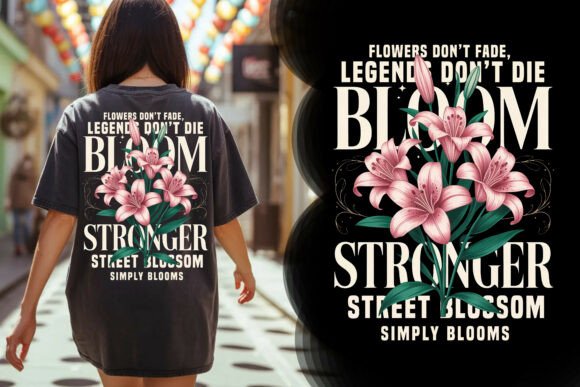
Bloom Stronger Floral Typography Tee
Bloom Stronger Floral Typography Tee – Avaliação Completa
Se você procura uma peça que una estilo contemporâneo, mensagem inspiradora e qualidade de impressão impecável, a Bloom Stronger Floral Typography Tee é a escolha certa. Este T‑shirt destaca‑se não apenas pela estética, mas também pelo storytelling visual que ele carrega: flores de lírio delicadas combinadas com tipografia ousada que celebra o crescimento pessoal e a resiliência.
Principais Pontos Positivos
- Design exclusivo – A frase “Flowers Don’t Fade, Legends Don’t Die” traz um toque motivacional que ressoa com quem busca superação.
- Equilíbrio visual – O contraste entre o floral suave e a tipografia forte cria um look elegante, ideal para streetwear, casual ou presente.
A Bloom Stronger Floral Typography Tee entrega exatamente o que promete: uma combinação harmoniosa de beleza delicada e força inspiradora. Com alta definição, fácil aplicação e um slogan que motiva, este design tem grande potencial de venda e de engajamento nas redes sociais. Não perca a oportunidade de oferecer um produto que celebra o crescimento pessoal enquanto mantém o estilo moderno.